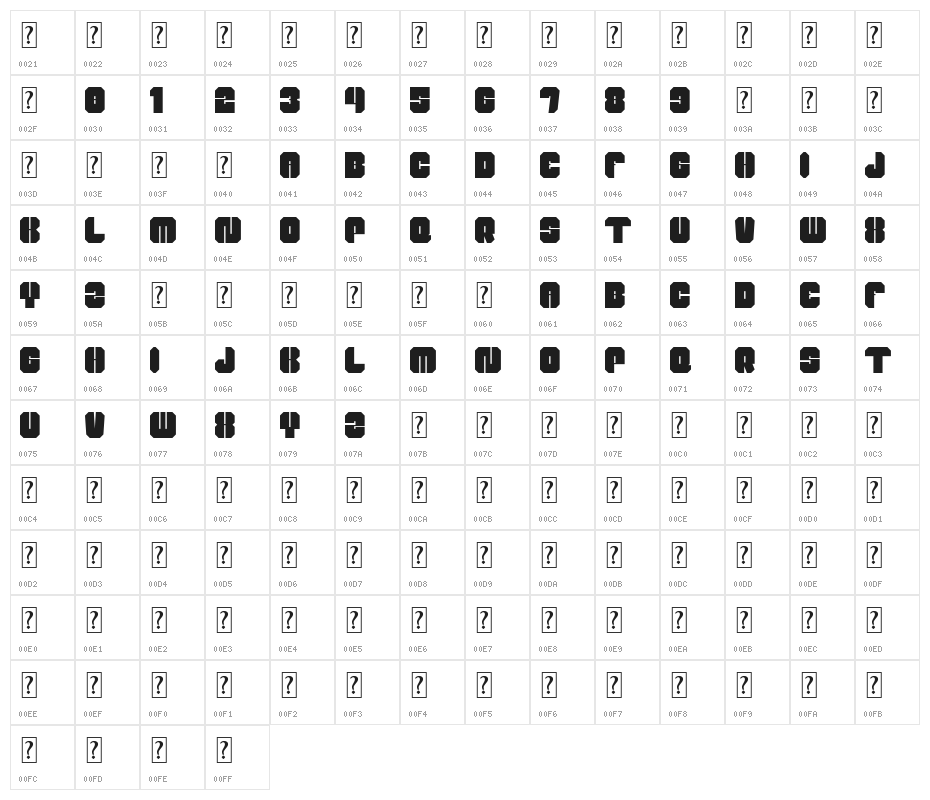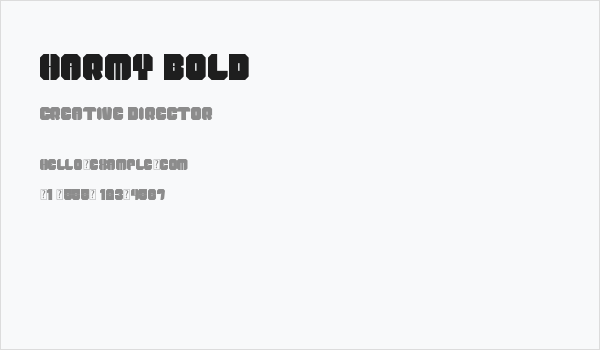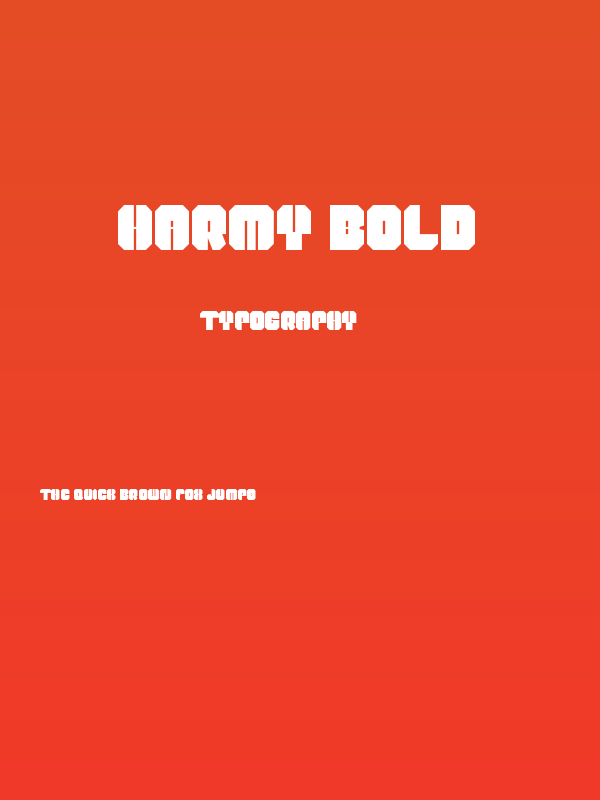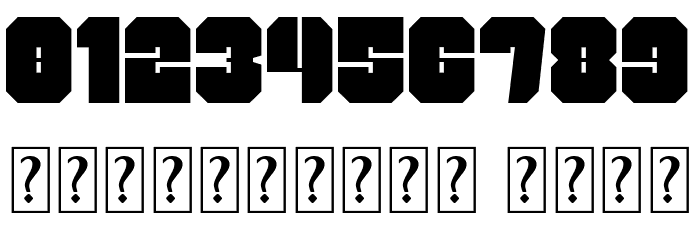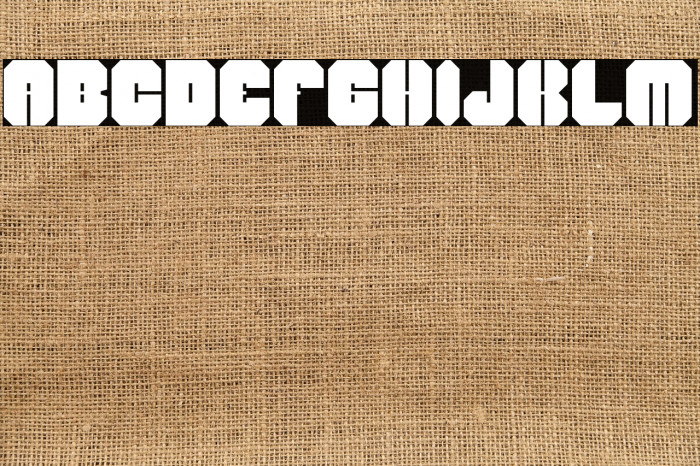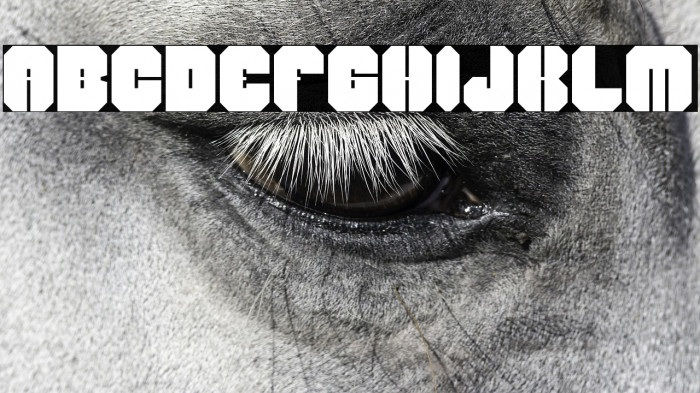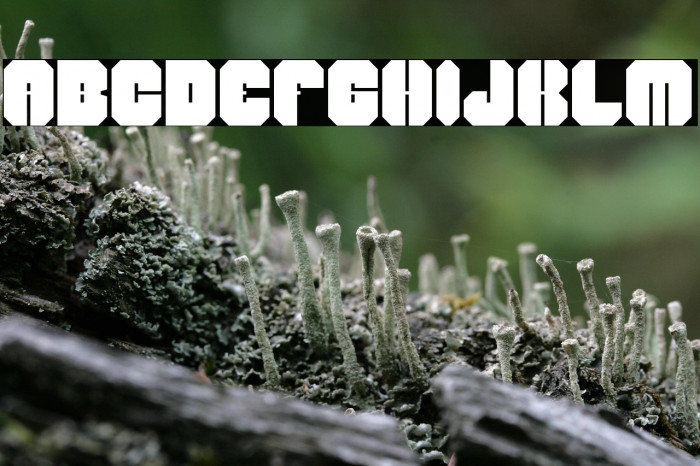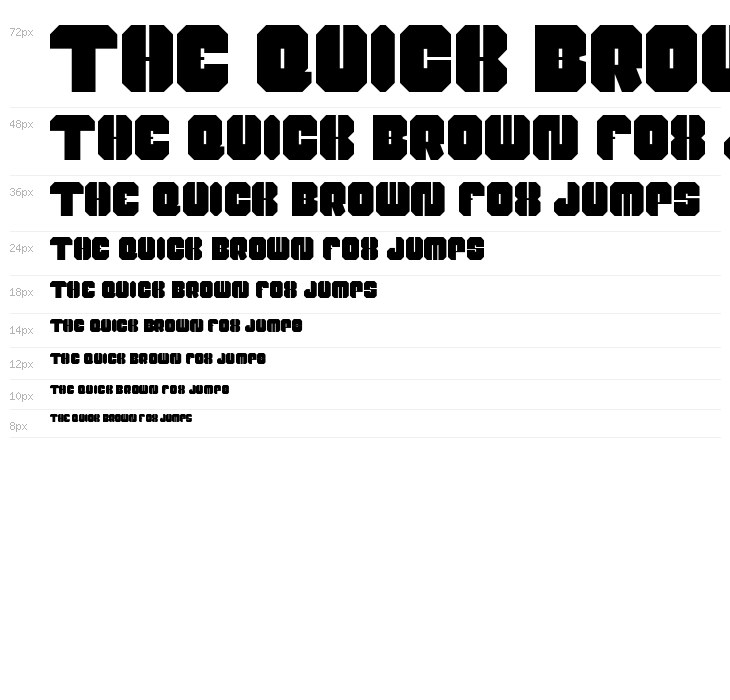
Harmy Bold Font
✎ Thick
Fonts by DaeDesign
| Schriften Familie | Harmy |
| Kategorien | Thick |
| Vorgeschlagene Projekte | Ideal for branding, posters, and signage where a strong, modern look is desired. |